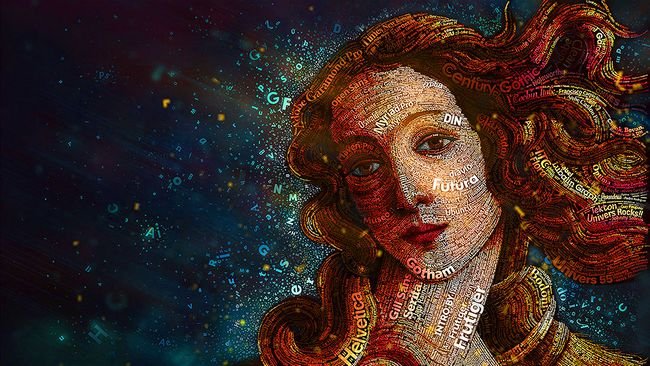
Para quem gosta de tipografia, as ilustrações de Dylan Roscover são de encher os olhos.
Dylan mistura várias palavras e fontes de tamanhos e formatos diferentes. A escolha dos elementos sempre tem um sentido específico para cada obra.
Alguns de seus trabalhos retratam famosas personalidades como Barack Obama, Mitt Romney, Steve Jobs e o autor russo Boris Strugatsky.
Além dos retratos, Roscover também produziu uma ilustração sobre a Coca-cola, em que juntou vários tweets sobre a marca em uma só obra. Em um de seus trabalhos, também se pode ver Vênus, a deusa do amor na mitologia romana.